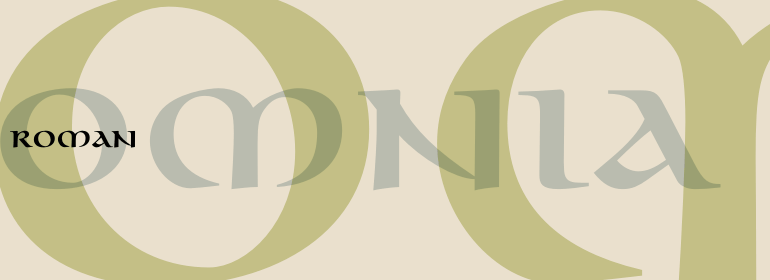
Omnia™
Omnia™,这款字体结构工整、笔画清晰,兼顾美观与易读性,适用于标题、正文、海报、包装、LOGO 等多种场景。字形优雅稳定,风格百搭耐看,适配日常排版与创意设计,让文字呈现更舒适、更具质感。Omnia™一笔一画,皆是细节,以均衡的比例、流畅的线条打造舒适视觉体验,字形端正大气,风格简约现代。无论是商业设计、品牌宣传还是日常排版,都能轻松驾驭,让文字更有格调与力量。Omnia™字体下载。
字体品牌: Linotype(Monotype) 设计师:Hoefer,Karlgeorg 字体分类:书法体、哥特体 字体属性:外文 字符集:Unicode 发布时间: 2018